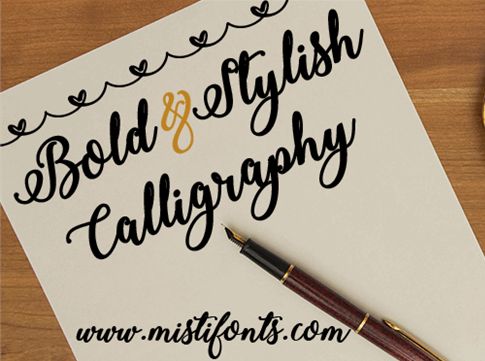
Bold Stylish Calligraphy Font – Download Grátis
Esta fonte de escrita épica é perfeita para quem busca dar um toque especial a seus trabalhos de escrita estilizada. Disponível no gosto do estilo elegante da Misti’s Fonts, esta fonte é ideal para designers que desejam adicionar uma mão-dadivada e sofisticada à suas criações digitais. Perfeita tanto para criação de logotipos quanto para adicionar um toque artesanal a texturas ou gráficos em movimento, esta fonte oferece contornos levemente curvos que tornam qualquer tipo de projeto mais envolvente. Com uma paleta cuidadosamente selecionada de linhas e sublinhadores, você pode personalizar sua mensagem para criar um estilo único. Neste ambiente digital vibrante, a fonte Bold Stylish Calligraphy Font é uma escolha perfeita para quem deseja dar vida à escrita estilizada. Composta por Misti’s Fonts, esta fonte oferece a combinação perfeita de elegância e criatividade, transformando simples textos em obras que transpiram estilo e personalidade. Descubra o poder desta fonte de escrita épica e deixe seu trabalho destacar-se. Tente agora e faça sua marca brilhar nas páginas digitais!